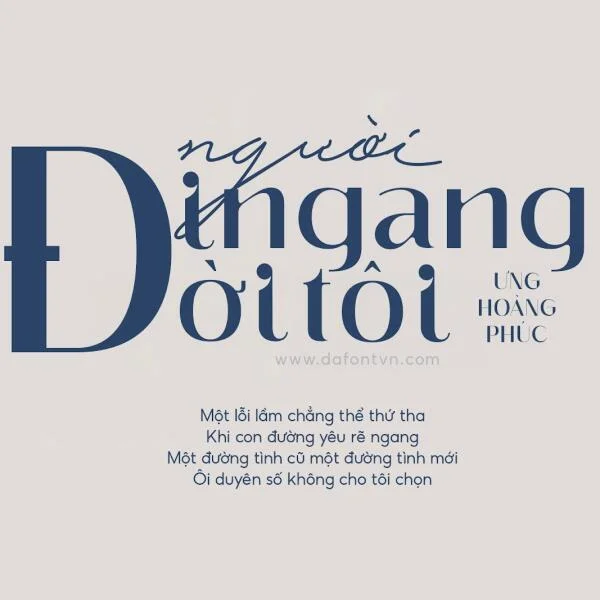
Font Appears - một kiểu chữ serif hiện đại và thanh lịch được sản xuất bởi Letterhend Studio
Tổng quan về Font Appears
Font Appears là một kiểu phông chữ hiện đại, tối giản mang phong cách gọn gàng và kiểu dáng đẹp. Xen kẽ phong cách và chữ ghép làm cho phông chữ trở nên độc đáo hơn và nổi bật trong các thiết kế.
Appears trông tuyệt đẹp trên lời mời, thiệp cảm ơn, báo giá, thiệp chúc mừng, logo, danh thiếp và mọi thiết kế khác cần có sự sáng tạo.
Appears font
Font Appears việt hóa
Font việt hóa Appears hiện đại
Font việt hóa đẹp typography
Chi tiết ký tự của Font Việt hóa Appears
Font Appears việt hóa phù hợp với các thiết kế khác nhau như thiệp mời, nhãn, biểu trương, tạp chí, bao bì, thời trang, typography, quảng cáo... Ngoài ra font đi kèm với rất nhiều Glyph khác nhau để bạn có thể áp dụng và tạo ra thiết kế ấn tượng cho riêng mình.